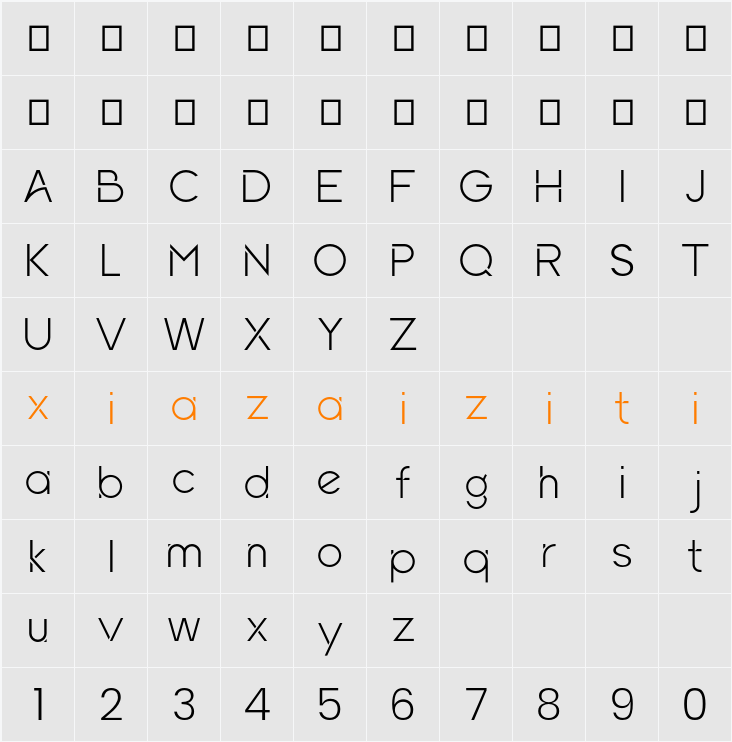
Xeroda
Xeroda,这款字体结构工整、笔画清晰,兼顾美观与易读性,适用于标题、正文、海报、包装、LOGO 等多种场景。字形优雅稳定,风格百搭耐看,适配日常排版与创意设计,让文字呈现更舒适、更具质感。Xeroda一笔一画,皆是细节,以均衡的比例、流畅的线条打造舒适视觉体验,字形端正大气,风格简约现代。无论是商业设计、品牌宣传还是日常排版,都能轻松驾驭,让文字更有格调与力量。Xeroda字体下载。